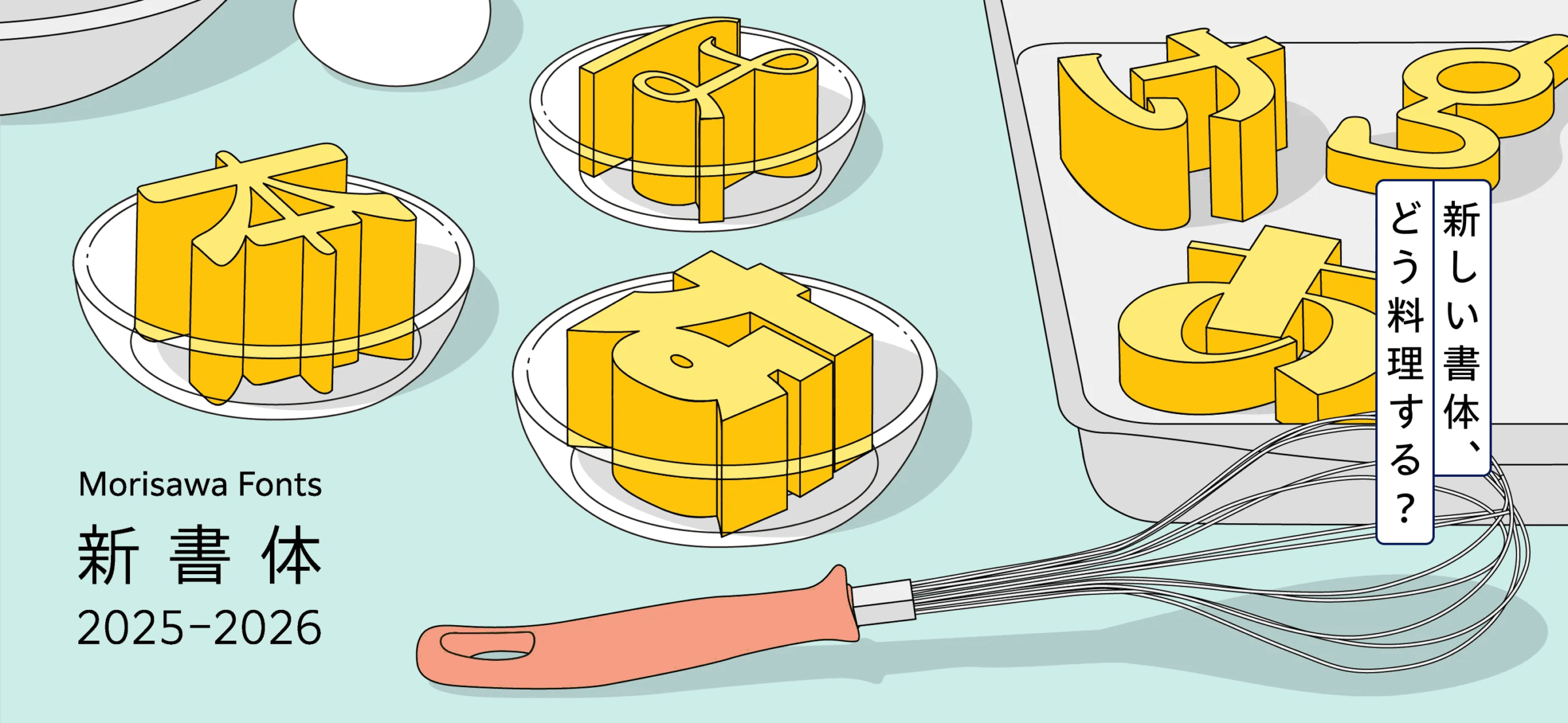
モリサワ 2月12日リリース「2025-2026年新書体第2弾」 多言語含む103ファミリーがMorisawa Fontsにラインナップ
株式会社モリサワは、2025-2026年の新書体第2弾を2月12日14時にリリースする 。今回のリリースでは、人気シリーズ「プフ」の新書体や多言語フォントを含む計103ファミリーがMorisawa Fontsのラインナップに加わる 。
和文フォントでは、2023年に毎日新聞社からリリースされた「瓦明朝」のゴシック体シリーズ「瓦ゴシック」が登場する 。さらに、デザイン書体「プフ」シリーズの新作「プフ ワンダー」や、毛筆の勢いを活かした「たらふく」「朝比奈」、中国の石拓の書に由来する「翠流魏碑」などが提供される 。
欧文・中国語・タイ文字など多言語ライブラリを大幅に拡充
欧文フォントでは、和文書体の明朝体から着想を得たセリフ体「Occupant Oldstyle」や、力強いサンセリフ体「Antenna」など計39ファミリー405フォントが追加される 。
中国語フォントでは、Arphic Typesの筆書系・デザイン書体29ファミリーに加え、現代中国の印刷書体の源流を築いた上海印刷技術研究所の簡体字フォント4ファミリーが新たにMorisawa Fontsからリリースされる 。また、タイ文字についても、DB DesignとCadson Demakのフォントが計26ファミリー拡充され、ベーシックなものからユニークなデザイン書体まで幅広くラインアップしている。
最新版の書体見本帳が完成し書店販売も開始
新書体2025-2026を掲載した最新の書体見本帳「表現・特徴で見つけるフォント BOOK Morisawa Fonts 書体見本帳 2025-2026」も完成した 。同見本帳は今後、モリサワが参加するイベントで配布されるほか、2月16日からは株式会社マイナビ出版より特製カバーつきの別装丁版が全国の書店で発売される 。